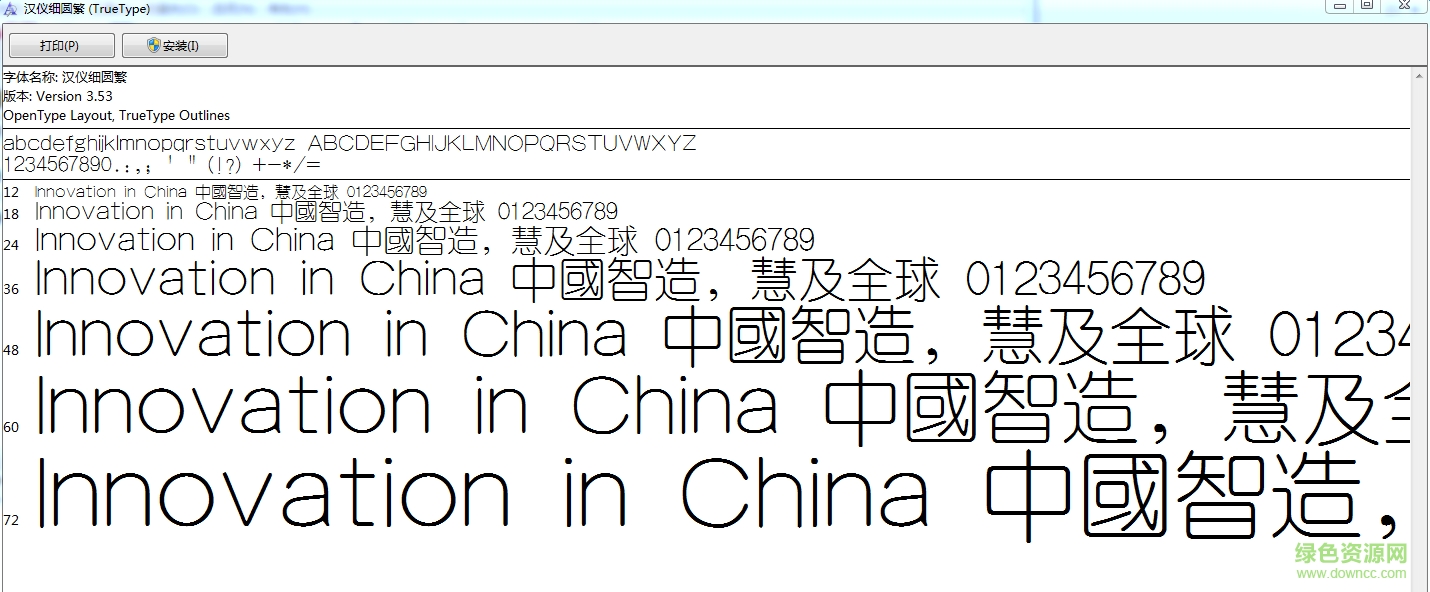
漢儀細(xì)圓繁體
漢儀細(xì)圓繁字體是一款漢儀類細(xì)長圓形風(fēng)格繁體字體軟件,圓形繁體字給人非常現(xiàn)代國際化的感覺,非常適合廣大書法家的喜愛,同時(shí)也適合年輕人的書法學(xué)習(xí),還有更多好看字體盡情期待,歡迎到綠色資源網(wǎng)下載體驗(yàn)!